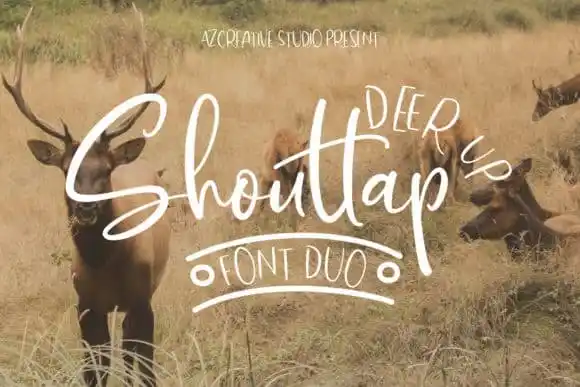
DeerUp Shouttap Font Duo – Download Grátis
A fonte DeerUp Shouttap Font Duo é uma combinação poderosa e feminina que inclui um script autêntico e uma tipografia sans-serif maravilhosamente lisa. Essa beleza retrata a escrita manual, combinando perfeitamente com as formas geométricas do tipo de calligrafia. Esta font é não apenas bela para uso em design gráfico, mas também oferece um leque vasto de possibilidades, incluindo logotipos, papelaria, rótulos e até mesmo assinaturas e convites para casamentos. Com extras adoráveis e caracteres PUA codificados, esta font proporciona versatilidade para que você realize seus projetos design em um nível elevado. Seja este o seu próximo projeto: com DeerUp Shouttap Font Duo, a sua ideia pode realmente soar linda e sofisticada.